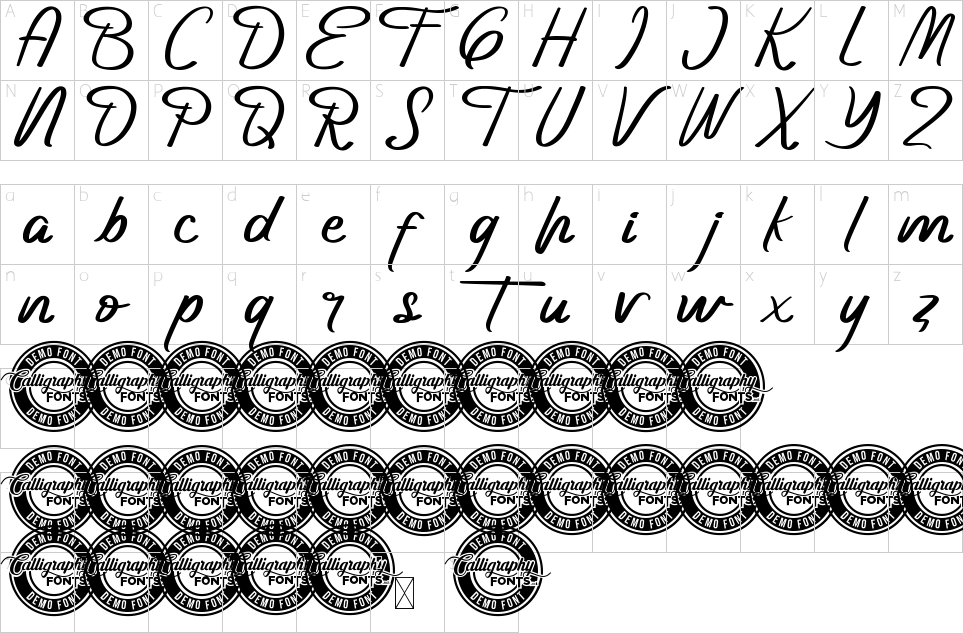
A Geistown Font é uma elegante escolha para quem busca aperfeiçoar seu design editorial ou adicionar um toque personalizado às suas criações digitais. Desenhada pela CalligraphyFonts, esta fonte proporciona linhas finas e leves que se adaptam perfeitamente ao texto, criando um contraste visual sutil mas eficaz. Confortável tanto para quem trabalha no ambiente Windows quanto no Mac, a Geistown é uma ótima opção para criar design gráfico com certeza de qualidade. Apesar de não ter detalhes específicos sobre seu estilo único ou funcionalidades únicas, o fato dela ser popular entre os usuários demonstra sua capacidade de adaptar-se a diferentes estilos e formatos. É uma fonte gratuita disponível para download que merece atenção por quem busca um design gráfico sofisticado sem comprometer no custo.